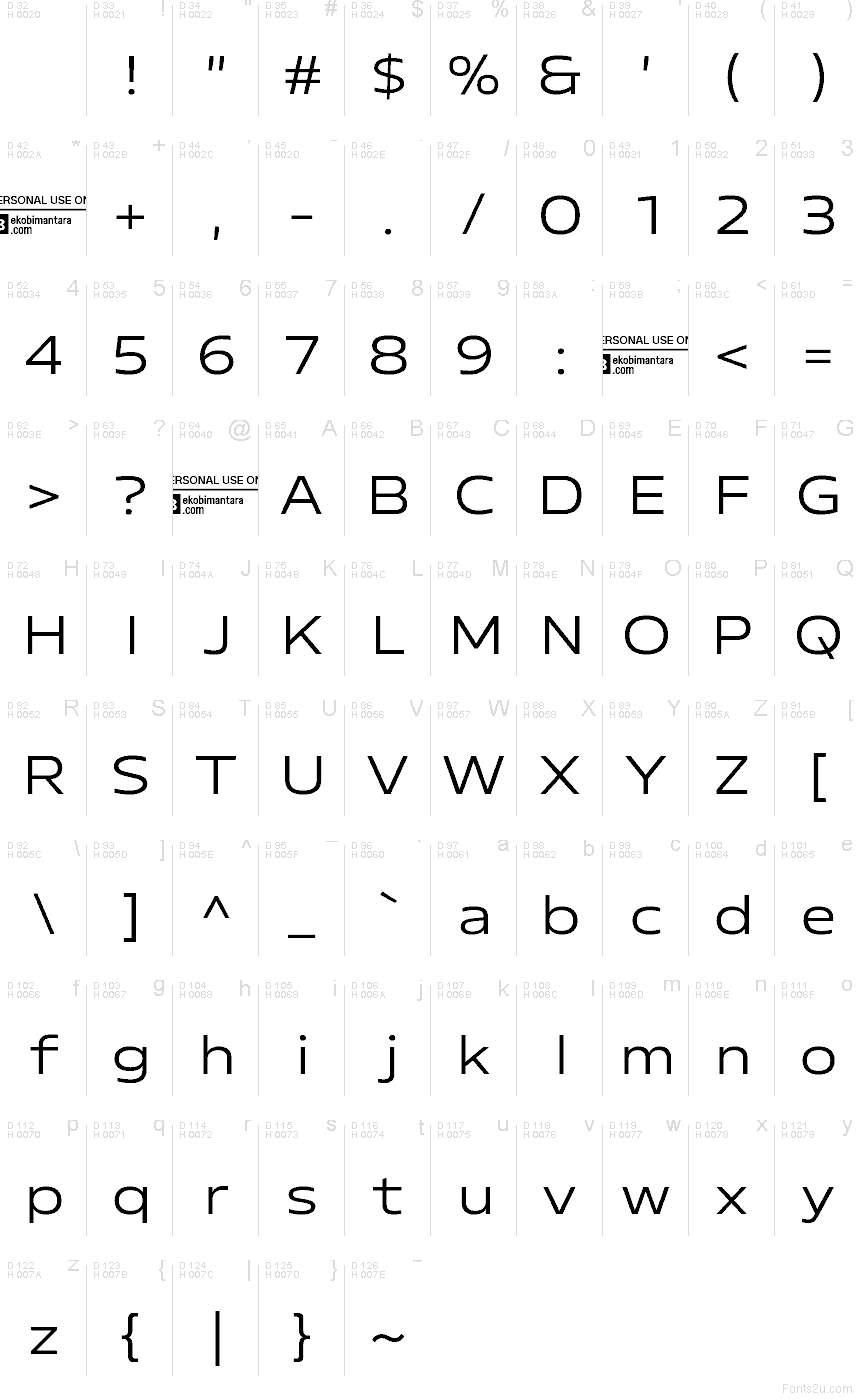
Profa Expanded par Eko Bimantara est une police sans empattement géométrique gratuite, au rythme calme et aéré, dotée de coins délicatement arrondis. Les lettres sont épurées et contemporaines, avec des courbes généreuses et des jointures nettes qui confèrent à la police une présence élégante et sobre, loin de l'aspect technologique rigide.
Elle s'adapte parfaitement aux systèmes de branding, aux couvertures de magazines, aux packagings, aux en-têtes d'applications et aux titres, pour un rendu moderne qui reste accessible. En tant que police gratuite, elle est idéale pour les titres courts et les logos, car ses formes circulaires et ouvertes confèrent une allure harmonieuse et légère, même sur des textes brefs.